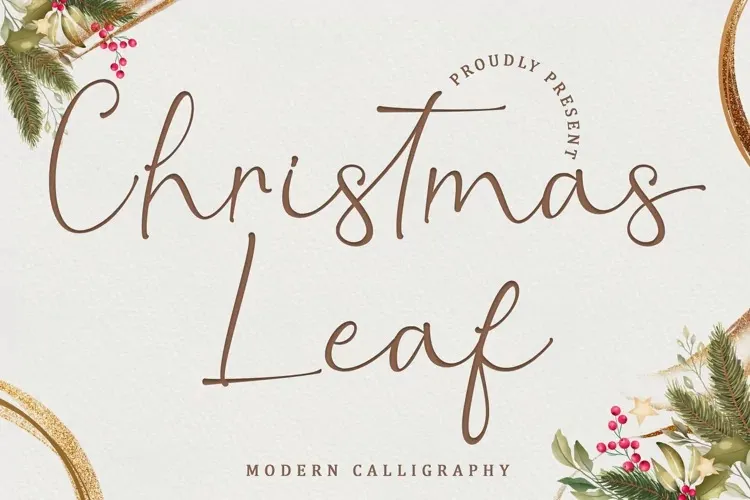
Esta fonte é uma outra delicada e moderna tipografia script que combina a essência de escrita clássica com um estilo atual. Ideal para ideias criativas, essa font pode destacar seu design. Christmas Leaf é pua encoded, o que significa que você pode acessar todos os símbolos e swashes sem dificuldade. Esta font script moderna não apenas adicionará uma pegada especial a seus projetos, mas também será um atalho rápido para criar versões distintas de letras. Compreender estas características poderia torná-lo mais fluente em trabalhos futuros que exigem essa tipografia. Adicione esta fonte à sua coleção e explore como ela pode transformar suas ideias em realidade, tornando-as ainda mais atraentes!